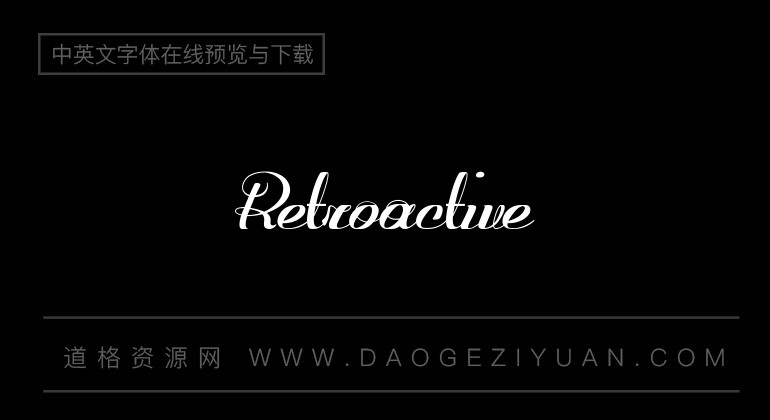
Retroactive
Retroactive 是一种字体,它具有很强的复古感和怀旧风格。它的设计灵感来源于 20 世纪 50 年代和 60 年代的手写字体,因此它具有相对宽大的字母间距、圆滑的曲线和饱满的笔画。这种字体的特点是带有一定的浪漫主义风格,具有一定的时代感和文化特征。 Retroactive 字体可以用于各种印刷和数字媒体设计,如海报、广告、商标、包装、书籍和杂志排版等。它可以为设计项目带来一种独特的视觉效果,使得设计更加突出和有吸引力。同时,Retroactive 字体也可以用于设计或品牌的标识,以强调品牌的独特性和历史渊源。 总的来说,Retroactive 字体是一种非常有特色和魅力的字体,适用于各种设计和排版需求,可以为设计师和品牌主带来不同寻常的体验和效果。
Retroactive是一款非常不错的手写艺术字体,具有很好的视觉感,适合于文化类的宣传设计、商业类品牌的广告和产品包装设计以及个性化文字排版等较多场景。